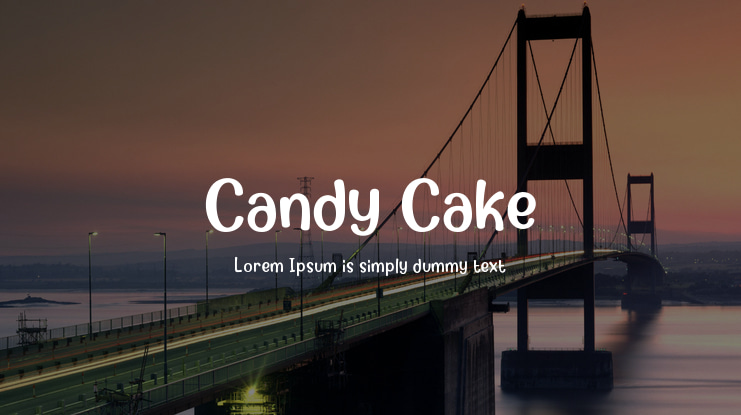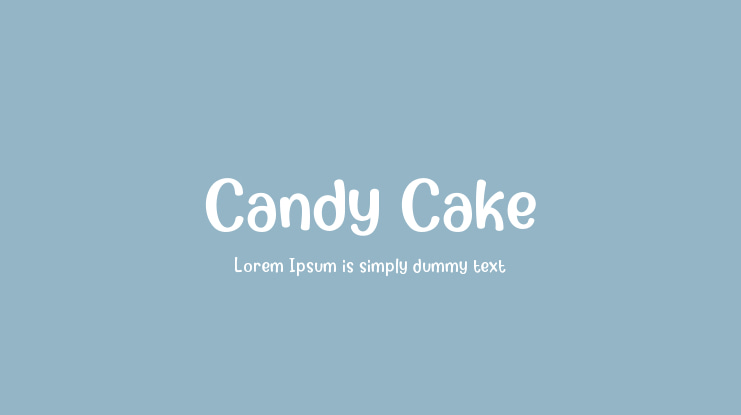
Font Candy Cake Việt hóa là bộ phông chữ thuộc dòng Display mang phong cách ngọt ngào, mập mạp và tràn đầy hương vị kẹo ngọt, được lấy cảm hứng từ những lớp kem phủ frosting đầy màu sắc trên các chiếc bánh kem. Với cấu trúc nét chữ phúng phính, các góc bo tròn ngộ nghĩnh và diện mạo vô cùng “ngon mắt”, phông chữ này là lựa chọn tuyệt vời cho các thiết kế bao bì tiệm bánh sinh nhật, hộp kẹo sô-cô-la, nhãn dán trà sữa và các ấn phẩm hướng đến thiếu nhi. Doozypack.vn cung cấp link tải trọn bộ phông chữ chuẩn kỹ thuật, giúp bạn sở hữu Font Kẹo độc đáo này, hỗ trợ đầy đủ tiếng Việt để tự tin thiết kế bao bì và bộ nhận diện thương hiệu chuyên nghiệp.
Đặc điểm thẩm mỹ độc đáo của bộ font Candy Cake
Font Candy Cake không đi theo sự sắc nhọn của các phông chữ hình học; nó mang đến một ngôn ngữ thị giác đầy tính biểu cảm, vui nhộn và gợi nhắc đến thế giới đồ ngọt đầy màu sắc.
Phong cách Sugary & Bubbly ngọt ngào như kẹo bông
Đặc trưng lớn nhất của Font Candy Cake Việt hóa là hình khối chữ cái dày dặn, mập mạp và có độ căng phồng như những viên kẹo dẻo marshmallows. Cấu trúc chữ độc đáo này tạo ra một sức nặng thị giác vượt trội, giúp tiêu đề trên bao bì ngay lập tức chiếm trọn tâm điểm chú ý, kích thích vị giác và mang lại cảm giác thích thú cho khách hàng ngay từ cái nhìn đầu tiên.
Cấu trúc chữ mập mạp gợi cảm giác ngon miệng
Tất cả các điểm kết thúc và góc nối của Font chữ Candy đều được xử lý bo cong mượt mà, tạo hình giống như những giọt sô-cô-la đang tan chảy hoặc lớp kem bơ mịn màng. Thiết kế này tạo ra tâm lý an tâm, gần gũi và vui tươi, cực kỳ ăn ý với các thương hiệu bánh ngọt, quán kem tươi hoặc các nhãn hiệu tổ chức sự kiện tiệc tùng.
Ưu điểm nổi bật của bản Font Candy Cake Việt hóa
Khi ứng dụng các phông chữ ngộ nghĩnh vào thị trường trong nước, sự chỉn chu về dấu câu là yếu tố quyết định đến tính chuyên nghiệp của ấn phẩm:
- Khắc phục triệt để lỗi dấu tiếng Việt: Phiên bản Việt hóa đã được đội ngũ thiết kế trau chuốt thủ công từng dấu câu. Các dấu sắc, huyền, hỏi, ngã, nặng được vẽ căng mọng, bo tròn đồng điệu cùng thân chữ gốc, không gây cảm giác chắp vá hay đè nét làm mất tính thẩm mỹ.
- Hộp giấy đựng Bánh ngọt & Tiệm bánh (Bakery): Nét chữ phồng căng gợi cảm giác thơm ngon, rất hợp làm tiêu đề chính trên hộp bánh sinh nhật, hộp bánh cookie, túi đựng bánh mì hoặc hộp bánh kem.
- Tem nhãn dán Kẹo ngọt & Sô-cô-la: Tiêu đề thương hiệu in bằng Font Kẹo trên tem decal bóng tạo nên vẻ ngoài ngọt ngào, rực rỡ và kích thích vị giác của người tiêu dùng ngay trên kệ hàng.
- Bao bì quà tặng sinh nhật & Thiếu nhi: Dùng cho tên thương hiệu trên hộp đồ chơi, bộ xếp hình hoặc hộp quà tặng trẻ em, tạo sự hào hứng và vui tươi.
03 Lưu ý kỹ thuật khi in ấn với phông chữ béo tròn Candy Cake
- Kiểm soát hiện tượng tràn mực (Dot Gain) tại khe chữ nhỏ: Các khoảng hở bên trong chữ cái của Candy Cake (như chữ ‘e’, ‘a’) khá hẹp. Khi in trên giấy có độ thấm mực cao như giấy Kraft, mực có thể bị lan làm bít kín các lỗ hở này. Bạn nên giữ size chữ tiêu đề tối thiểu từ 10pt trở lên để bảo đảm độ sắc nét.
- Lựa chọn hệ màu Pastel ngọt ngào: Phong cách Candy Cake đẹp nhất khi phối cùng các tông màu Pastel (hồng phấn, vàng kem, xanh mint) hoặc màu rực rỡ tươi vui. Một đường viền (Stroke) mỏng quanh chữ cũng giúp tiêu đề trông “nổi” và sắc nét hơn trên vỏ hộp.